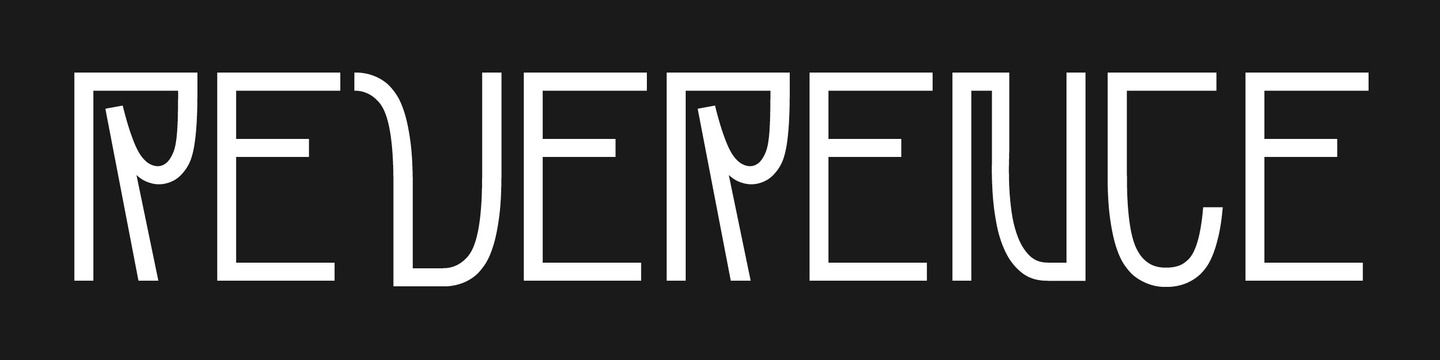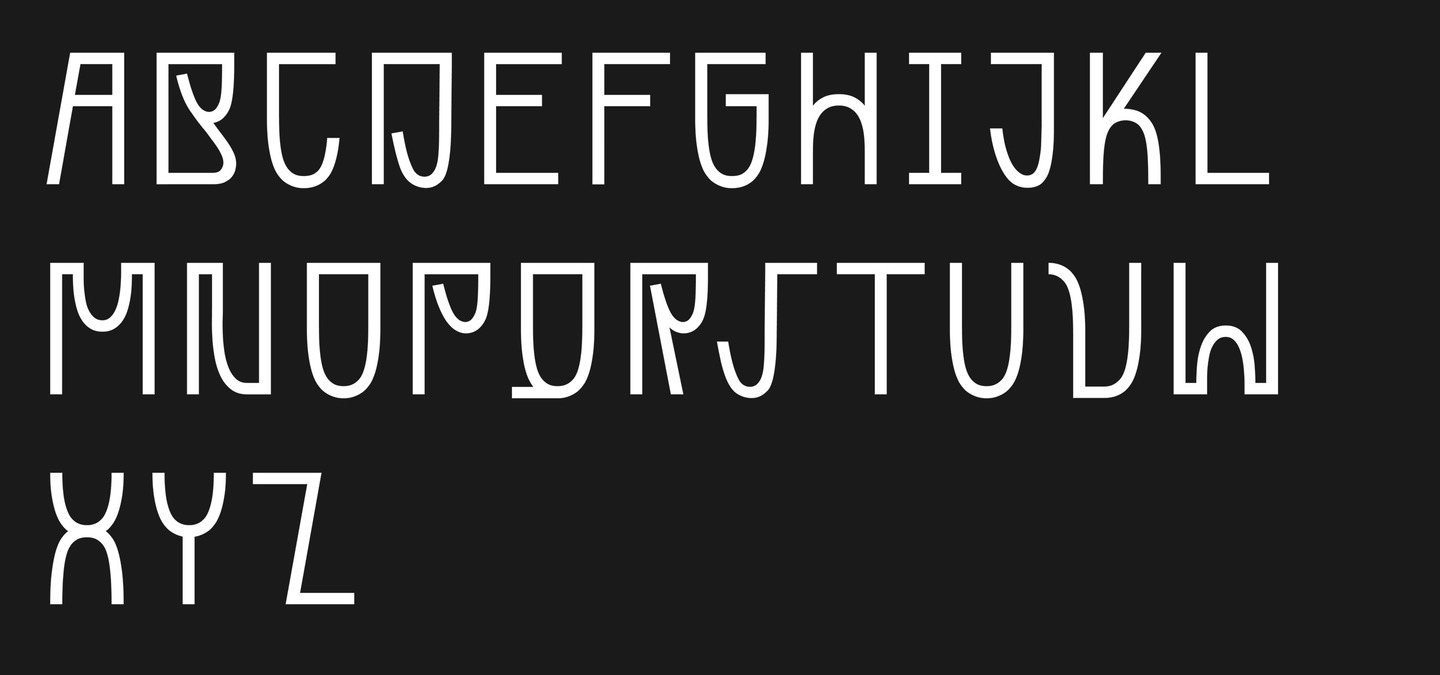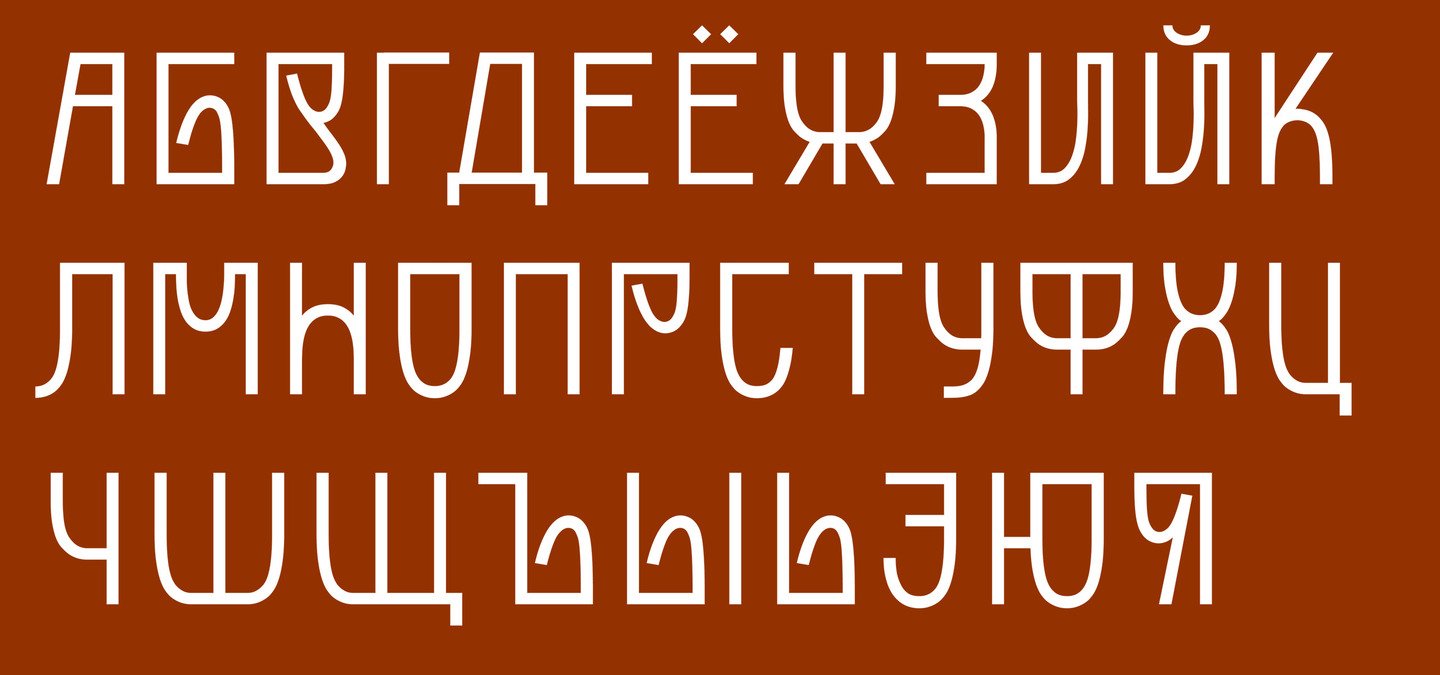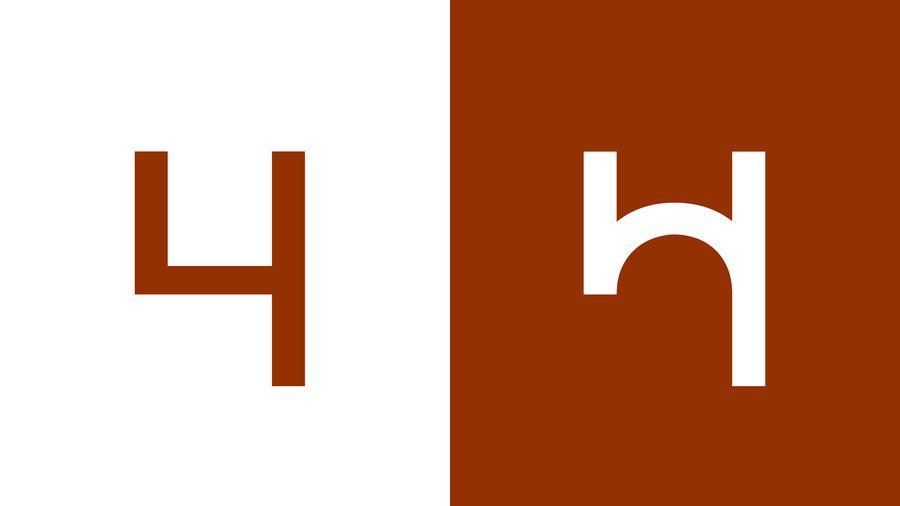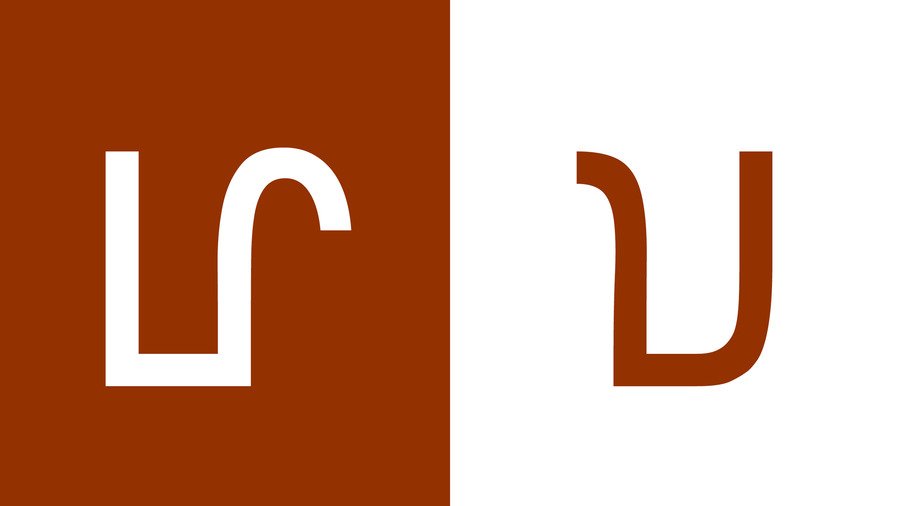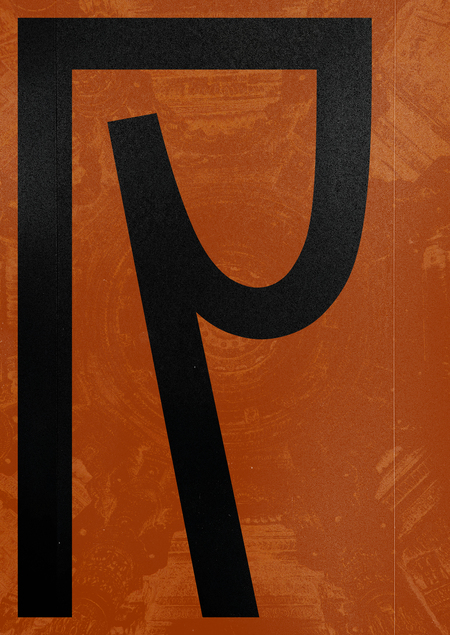
Шрифт Reverence вдохновлён визуальной культурой Индии и построен на сочетании геометрической структуры и пластики традиционных форм
Прописные знаки объединяет верхняя горизонталь и прямые углы, а округлые формы имеют плоское завершение, благодаря чему строка воспринимается как единая графическая конструкция
В основе гарнитуры лежит овал с резкими переходами. Он повторяется в конструкции большинства знаков, формируя внутренние просветы и общий ритм шрифта
Помимо основной кассы были разработаны альтернативные знаки с более декоративной пластикой
На основе гарнитуры был создан бренд ювелирных украшений Indra, вдохновлённый архитектурой Индии